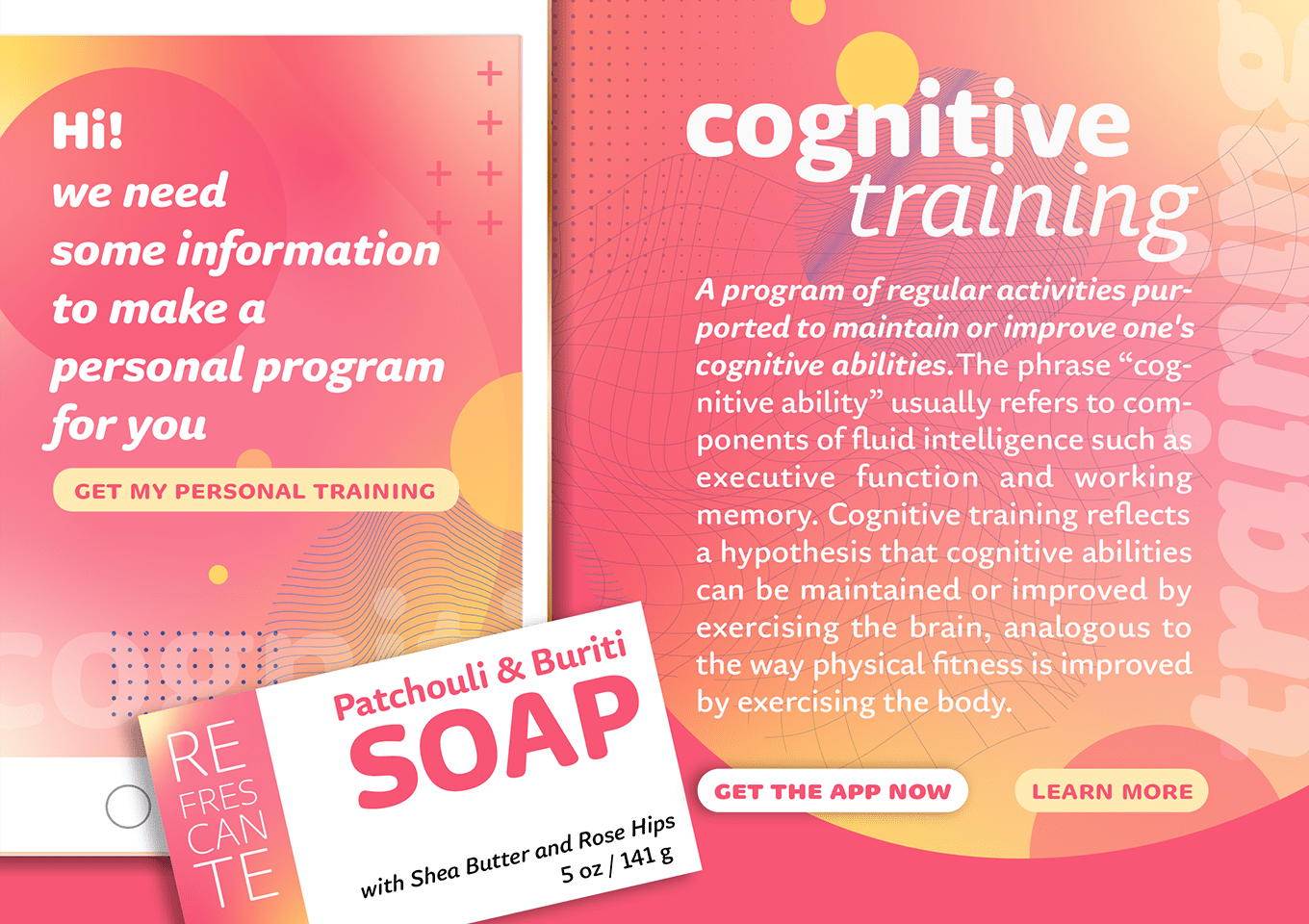
Roleは 、セリフ、サンセリフ、スラブセリフ、ソフト(ラウンデッド)の4つのスタイルと、Text(本文用)、Display(小見出し用)、Banner(大見出し用)の3つのサイズ別に最適化されたバリエーションを持つ、合計200書体のスーパーファミリー書体です。すべての書体は、「誠実さ」と「安定感」をコアイメージとし、Soft は「親しみやすさ」をテーマに制作されています。 Role Soft Bannerは先端や骨格の丸みを抑えた端正な大見出し用の書体です。